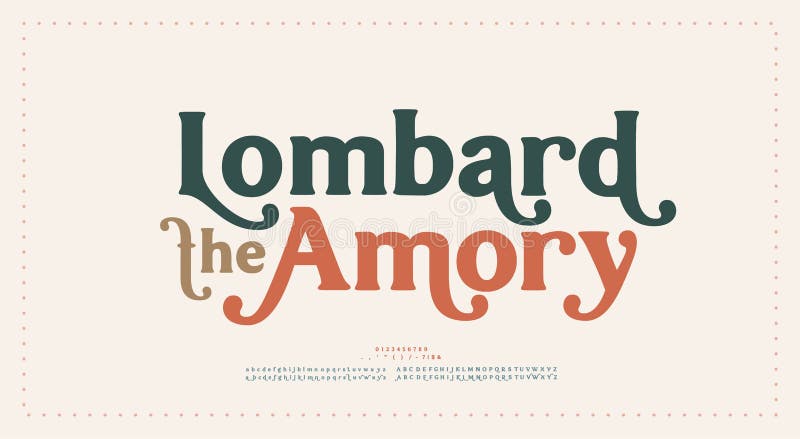
шрифт и число букв ретро-алфавита. typography элегантная роскошь классическая надпись serif декоративные шрифты свадебная концепция. векторная иллюстрация.